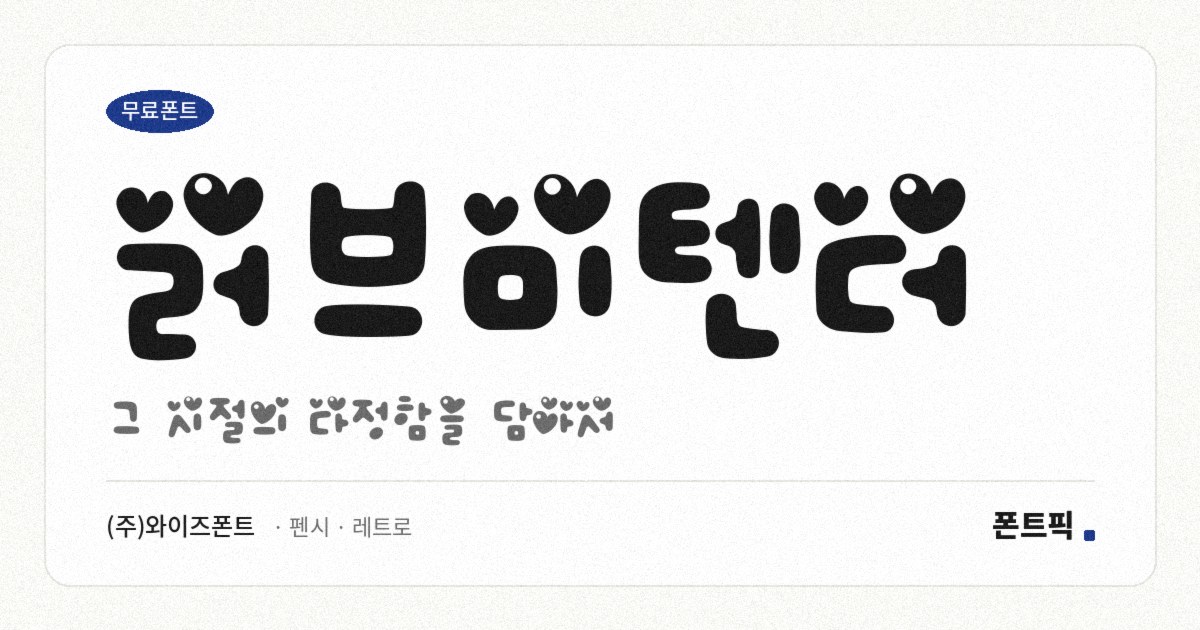
러브미텐더 서체 견본
러브미텐더
TDTDLoveMeTender
• 굵기1종 Regular
• 글자 수완성형 11,172자
• 분류펜시 · 레트로
러브미텐더 소개
와이즈폰트의 손글씨 서체로, 글자를 쓰는 것만으로 장식이 끝나는 종류입니다. 자음과 모음 사이사이에 하트가 박혀 있어서 가나 사 같은 글자에도 하트가 따라옵니다.
파일을 열어 보면 같은 회사의 손글씨 서체 가운데 획이 굵은 편에 속합니다. 가로획과 세로획의 굵기가 거의 같아 획이 고르고, 받침이 붙어도 높이가 크게 변하지 않는 네모틀이라 손글씨치고는 글줄이 가지런합니다. 낱자는 정사각형에 가깝습니다.
문제는 장식의 밀도입니다. 획이 굵은 데다 하트까지 들어가 있어서 문장이 길어지면 하트끼리 부딪혀 읽기 어려워집니다. 고백 카드나 기념일 배너처럼 한 문장짜리 자리에 쓰는 것이 맞습니다. 현대 한글 11,172자를 모두 담고 있어 어떤 글자를 넣어도 빠지지는 않습니다. 굵기는 하나입니다.